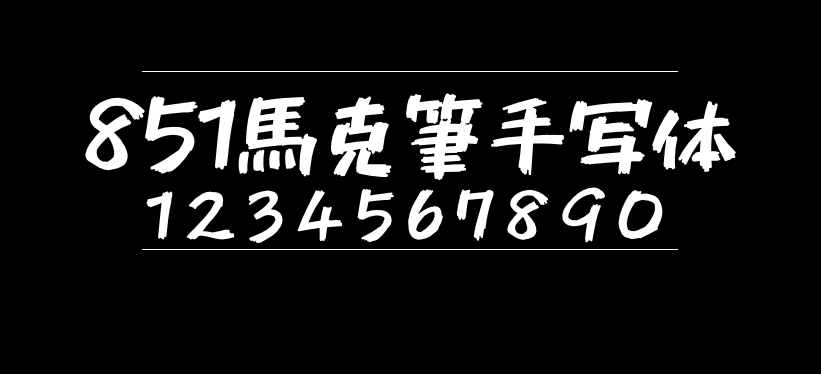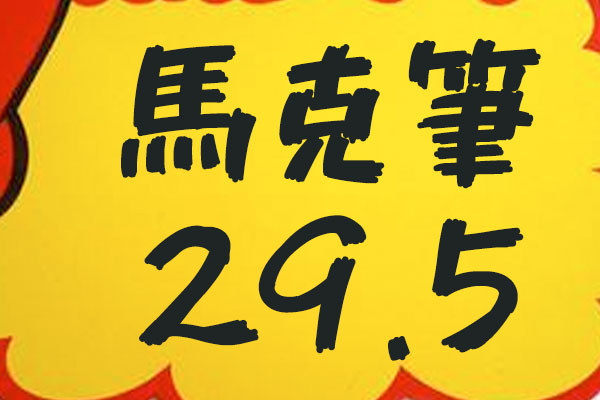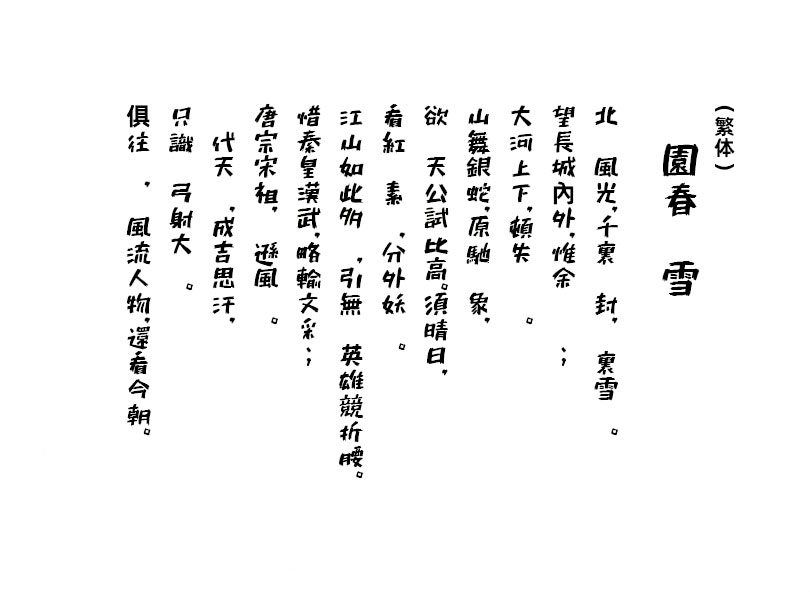
851马克笔手写体
851马克笔手写体(851チカラヅヨク-かなA、851CHIKARA-DZUYOKU-KANA-A)是日本设计师 8:51:22 pm 设计的字体,这个设计师昵称挺有个性的,估计是在这个时间点发生了一件令他印象很深刻的事吧!
这款马克笔手写体,横细竖粗,行笔飘逸,给人一种吐槽时的动画字幕的印象。不过支持的中文字符不算太多,要使用这一款字体还是要看运气了,如果有刚好需要的字体,还是很不错的,希望作者能补充更多中文字符。
当然了,如果用来绘制POP促销,只需要用到数字的话,不受什么影响,效果应该不错!
851马克笔手写体